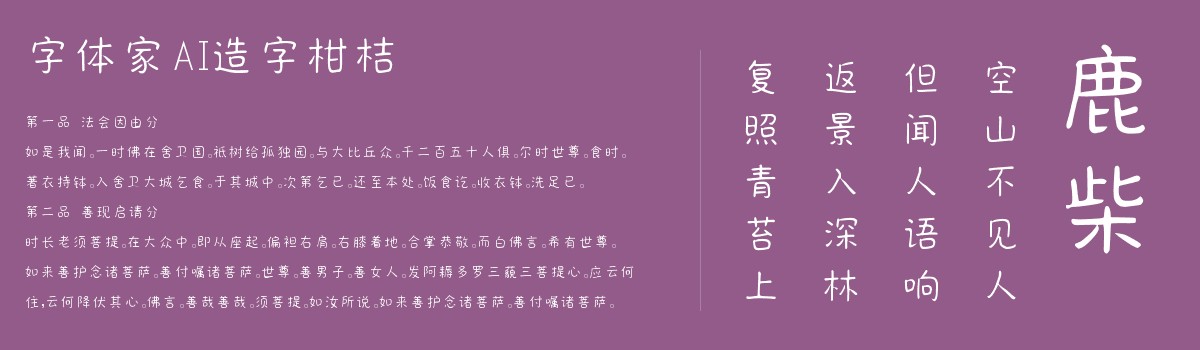
字体家AI造字柑桔
字体家AI造字柑桔是一款由字体家AI神笔造字生成的艺术字体,此字体为无衬线结构,笔画粗细均匀,线条流畅舒展。整体结构端庄均衡,每个笔画的起收笔处有细微的弧度过渡,不生硬,兼具现代简约的利落与手写般的柔和质感,易读性强,视觉上平和舒展,如春日微风拂过,给人温润舒适的感受。适合用于一些广告标题、平面文案、海报标题、网页广告用字的编辑。